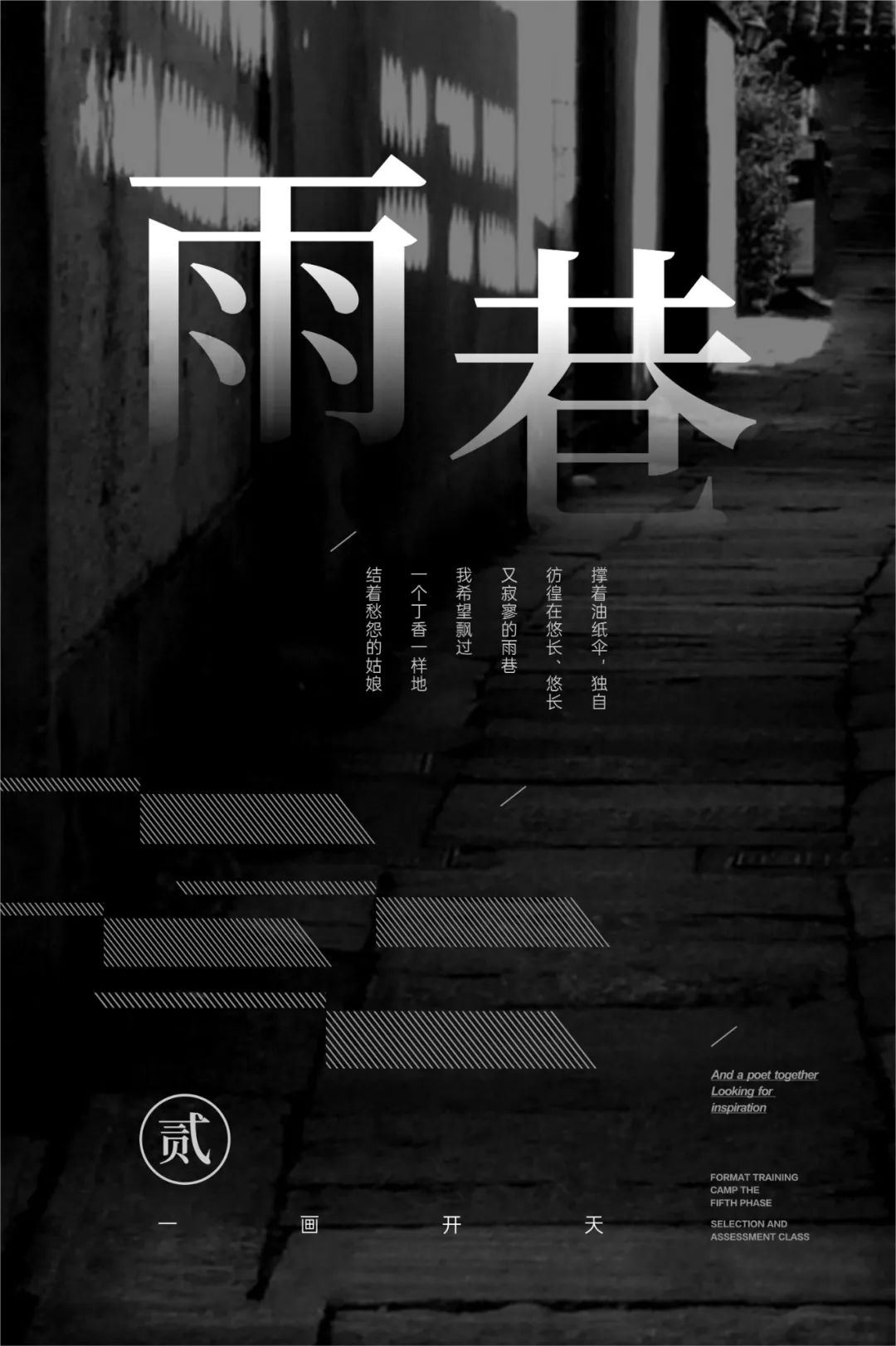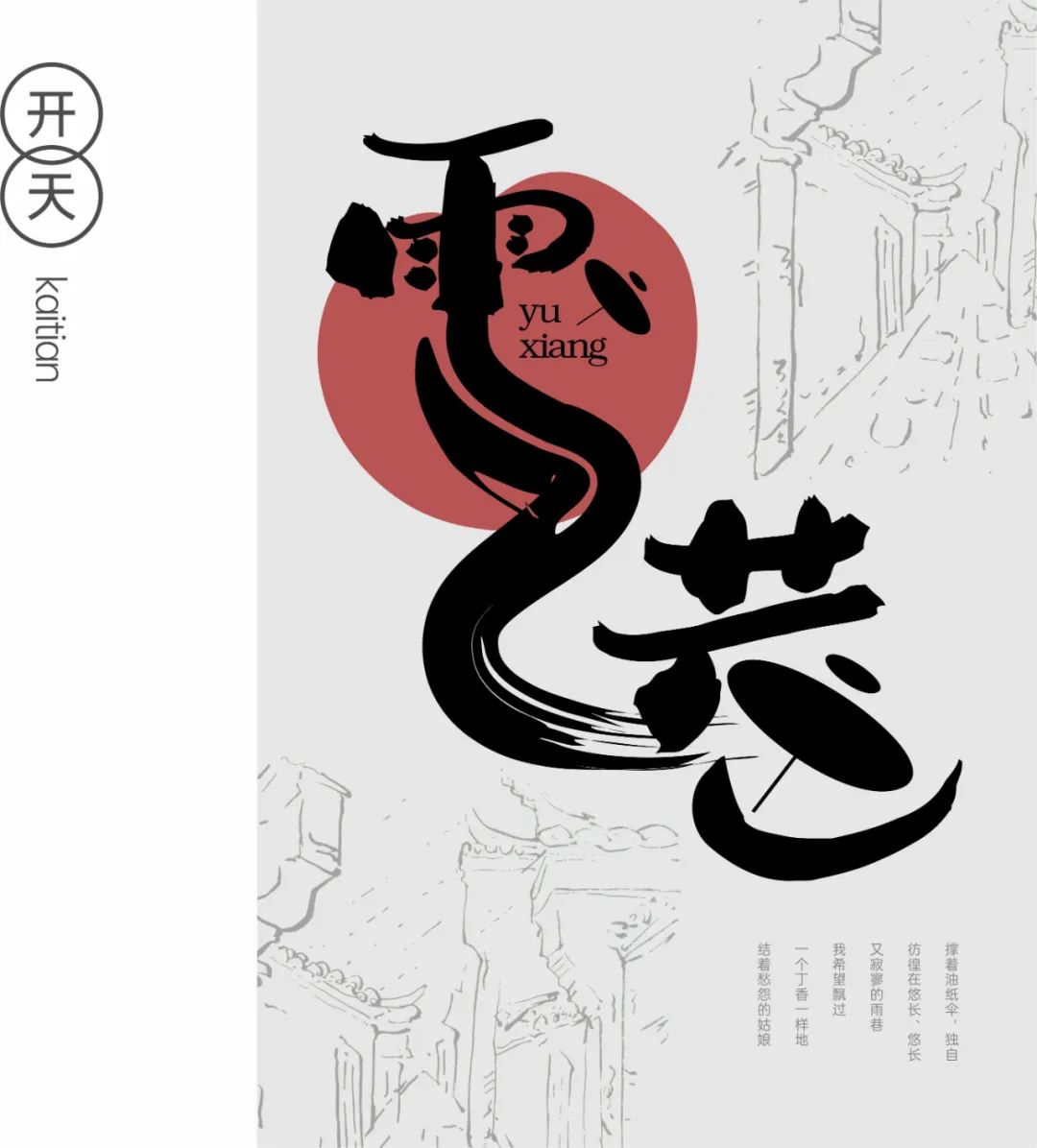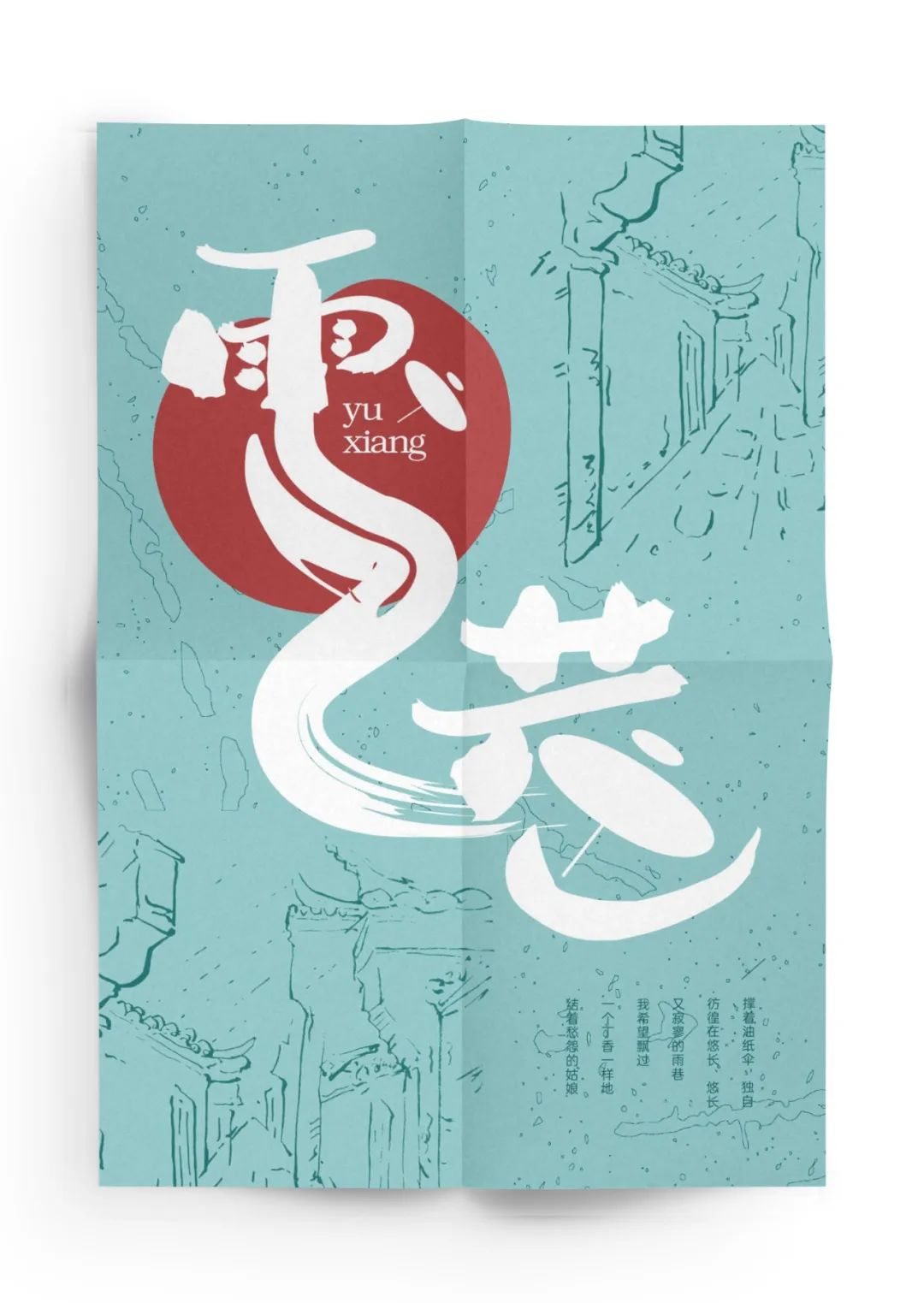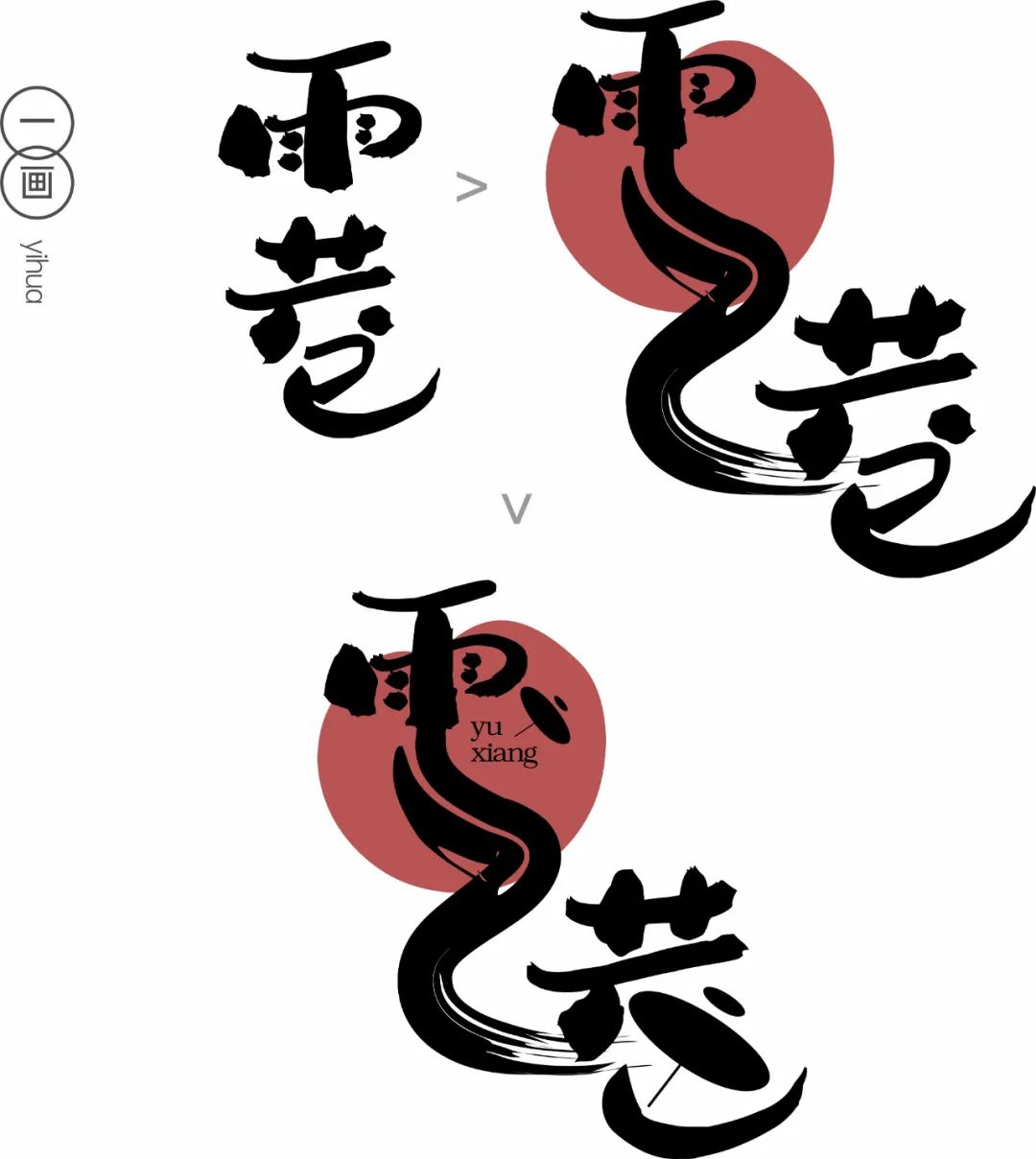
看完这个海报,竟然学会了标题设计
现代诗《雨巷》
文/戴望舒
撑着油纸伞,独自
彷徨在悠长、悠长
又寂寥的雨巷
我希望逢着
一个丁香一样地
结着愁怨的姑娘
她是有
丁香一样的颜色
丁香一样的芬芳
丁香一样的忧愁
在雨中哀怨
哀怨又彷徨
她彷徨在这寂寥的雨巷
撑着油纸伞
像我一样
像我一样地
默默彳亍着
冷漠、凄清,又惆怅
她默默地走近
走近,又投出
太息一般的眼光
她飘过
像梦一般地
像梦一般地凄婉迷茫
像梦中飘过
一枝丁香地
我身旁飘过这女郎
她静默地远了、远了
到了颓圮的篱墙
走尽这雨巷
在雨的哀曲里
消了她的颜色
散了她的芬芳
消散了,甚至她的
太息般的眼光
丁香般的惆怅
撑着油纸伞,独自
彷徨在悠长、悠长
又寂寥的雨巷
我希望飘过
一个丁香一样地
结着愁怨的姑娘
《雨巷》是中国诗人戴望舒1927年创作的一首现代诗。诗中描写了抒情主人公“撑着油纸伞”,独自彷徨在悠长而又寂寥的雨巷。他怀着一种缥缈的希望,希望逢着“一个丁香一样地结着愁怨的姑娘”,这个姑娘有着丁香一样的颜色与芬芳,而她的内心却结着忧愁、哀怨。他逢着了这样的姑娘,然而转瞬即逝,“像梦中飘过”,她的颜色、芬芳、“太息般的眼光”以及“丁香般的惆怅”统统消散在“雨的哀曲里”。他依旧“撑着油纸伞”,独自彷徨在悠长而又寂寥的雨巷,依旧怀着希望,希望飘过“一个丁香一样地结着愁怨的姑娘”。
《雨巷》中,诗人用象征性的意象及意象群来营建抒情空间,传达内心情感,并且融会了中国古代诗歌,尤其是晚唐五代纤弱婉约诗词的艺术营养。不仅如此,这首诗在艺术上的成功之处还在于它的和谐的音律美。
一画 >
标题雨巷选用具有手写文艺气质的字型,绘制出类似巷道的弯弯曲曲的笔触,将两字连接起来。
添加暗红色的不规则图形,寓意诗中传达的情愫,添加上油纸伞的剪影,替代笔画更有画面感。
速写画出巷子
根据诗意找寻巷子的图片,用速写的手法勾勒出雨巷的模样,比实物照片更加具备想象力与抽象感知力。
开天 >
最后一步是利用这些演变的具象事物根据情境构成一幅完整的画面,这个画面中有点,有线也有面。
字体与速写场景融合,如回忆般丝丝缕缕,若近又似远,迷迷蒙蒙,美好,惋惜与忧郁。
添加上斑驳的肌理,青色的色彩营造了更好的画面感,细雨,青苔,潮湿,回忆里的油纸伞。
诗人总结 >
有时候我们看设计只是设计,看到的不一定是好的,但是看不到的却总是能够左右画面,如同我们一画开天的专栏,可以从无形的诗词中找到韵律,进而生成我们设计的语言,去感受吧,那一点一线中的无形世界。